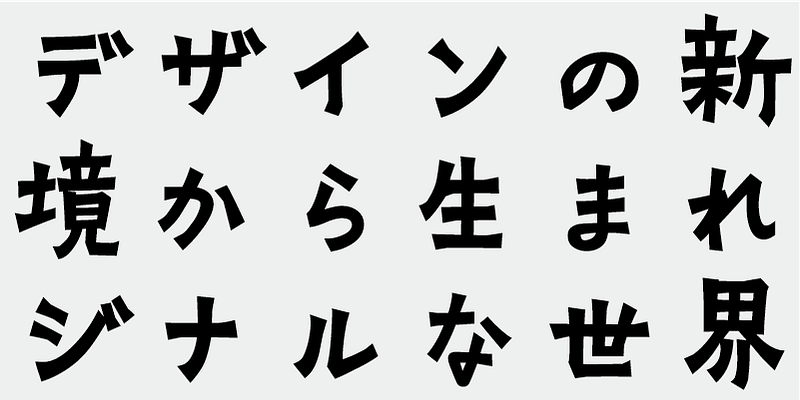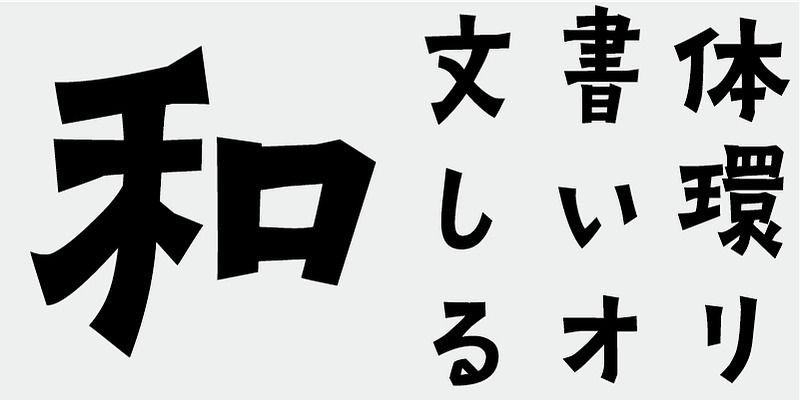
Esta tipografía fue diseñada haciendo referencia a los trabajos caligráficos de Jin Nong (calígrafo y pintor de la Dinastía Qing, China). Dependiendo del número de trazos, el tamaño del glifo de un carácter puede variar y los caracteres ofrecen un aspecto irregular y a la vez dinámico.
Esta fuente incluye los 1000 caracteres kanji principales elegidos de tablas de frecuencia de caracteres elaboradas por empresas de periódicos, editoriales e institutos de investigación lingüística, además de 206 caracteres kana y signos de puntuación.
En la producción de fuentes japonesas de hoy en día, los 7000 caracteres del estándar JIS se consideran esenciales. Pero, ¿todas las fuentes realmente necesitan 7000 caracteres? En la época de la fotocomposición, se necesitaban muchos menos caracteres. FONT1000, un grupo de diseñadores de tipos de letra independientes, comenzó con esa sencilla pregunta. Hemos seleccionado el mínimo de 1000 caracteres kanji (ideográficos) necesarios para la composición tipográfica en japonés y nos hemos esforzado en crear tipos de letra y fuentes de forma activa para admitirlos. Este conjunto de 1000 caracteres kanji se seleccionó utilizando datos de frecuencia de caracteres recopilados por empresas de periódicos, editoriales, organizaciones de investigación lingüística, etc., y también incluye caracteres silábicos kana y signos de puntuación. FONT1000 se formó en 2001 con 25 diseñadores y 25 tipos de letra. Hoy tenemos 130 tipos de letra y hemos crecido hasta incluir casi 40 miembros, lo que hace posible trabajar con tipos de letra con más caracteres.